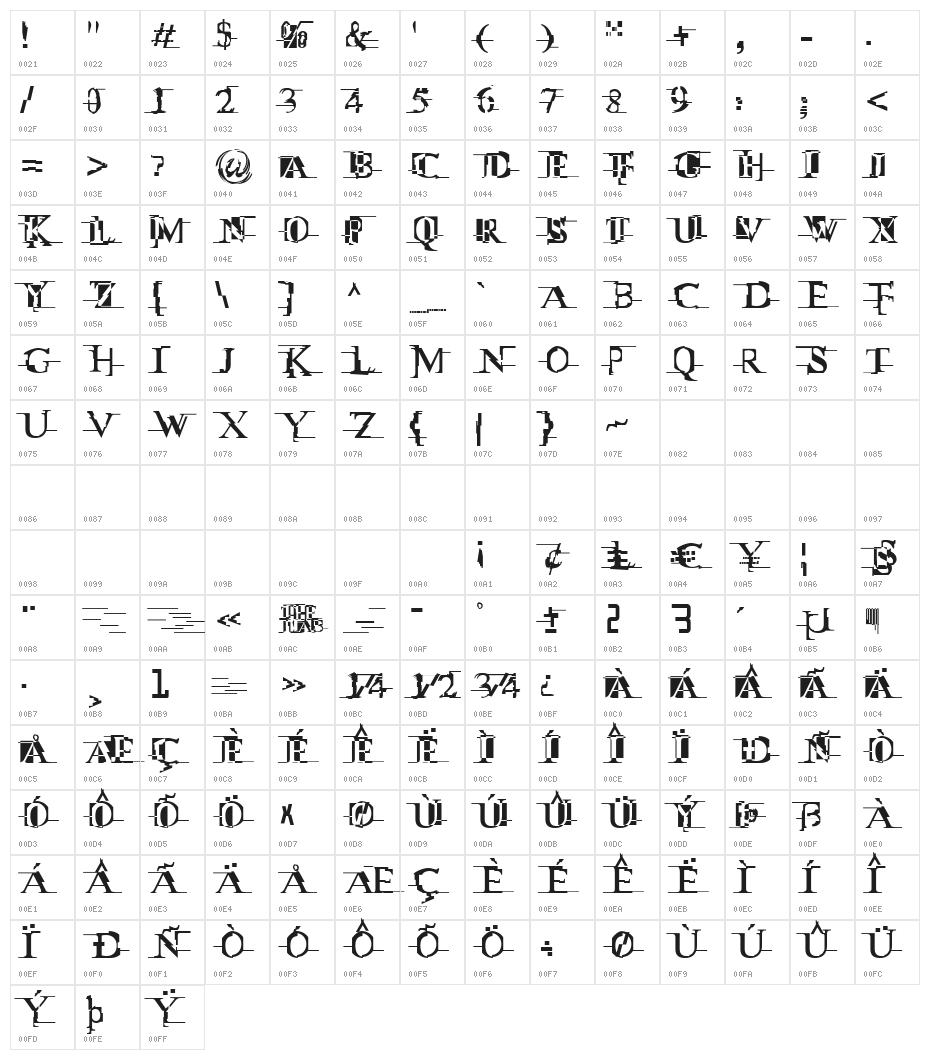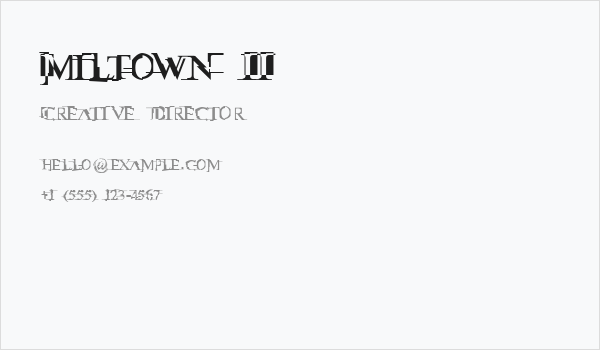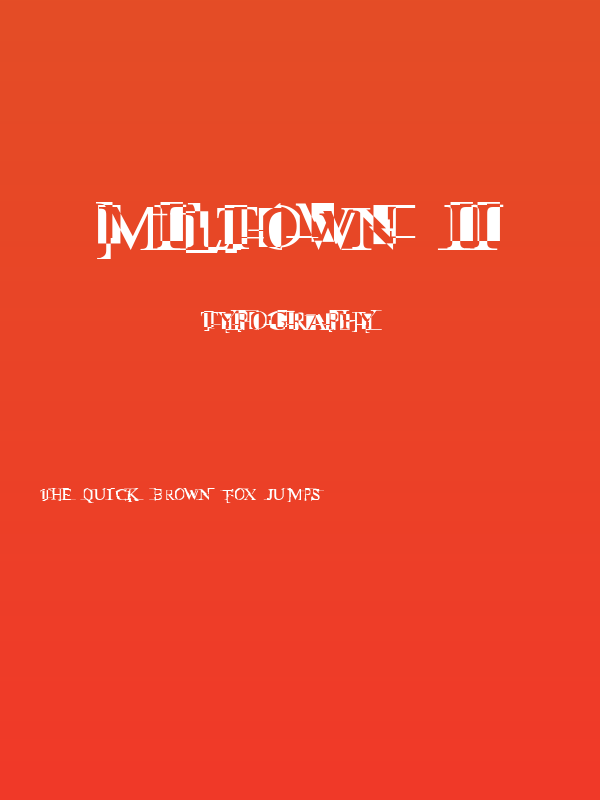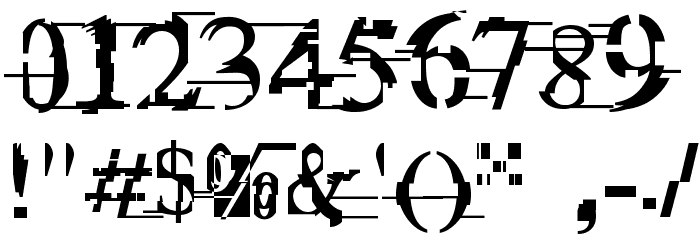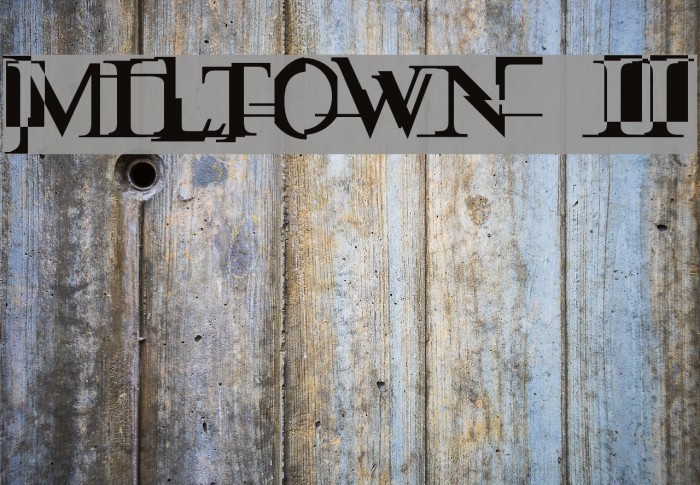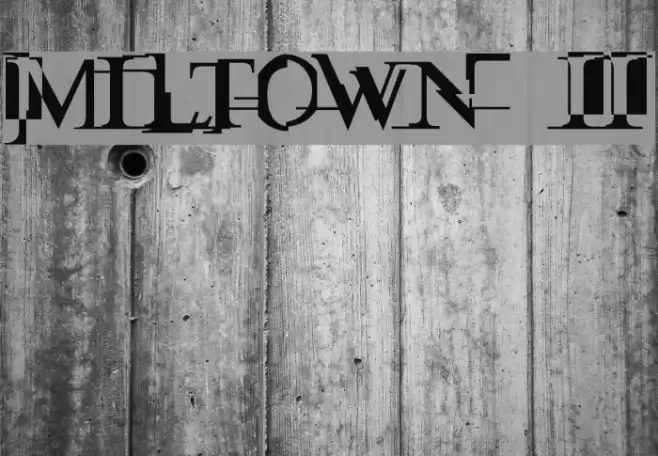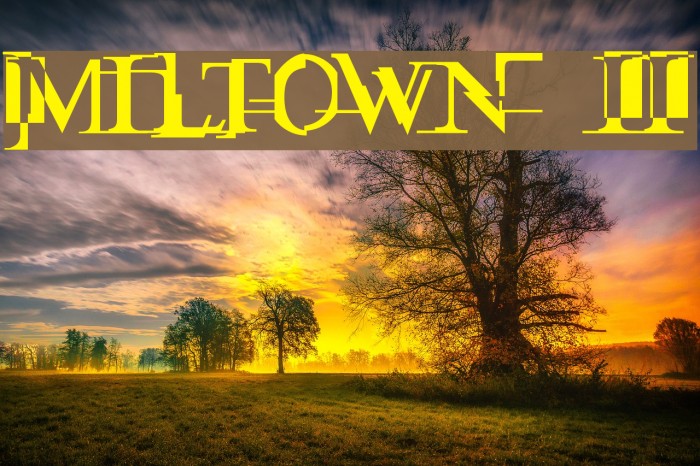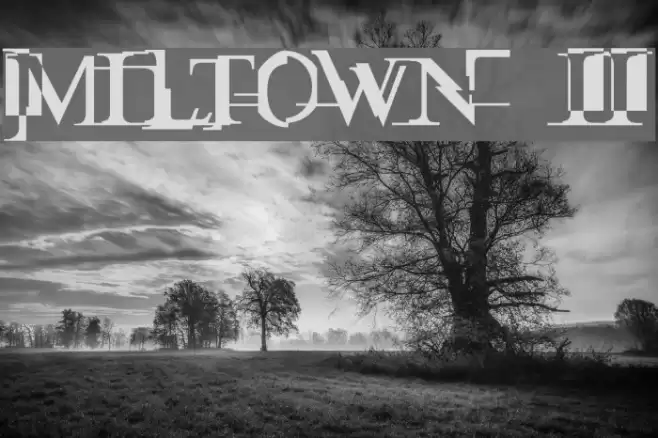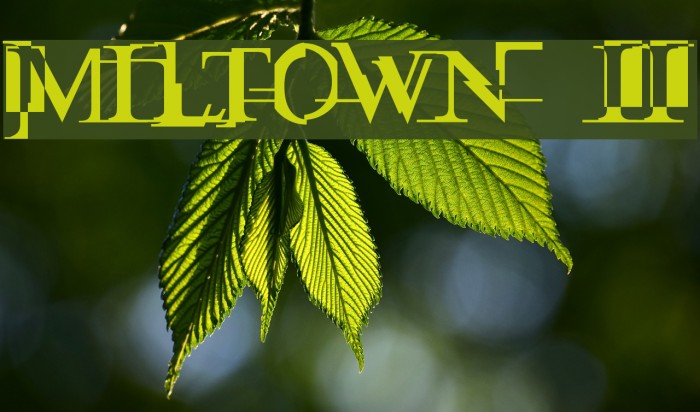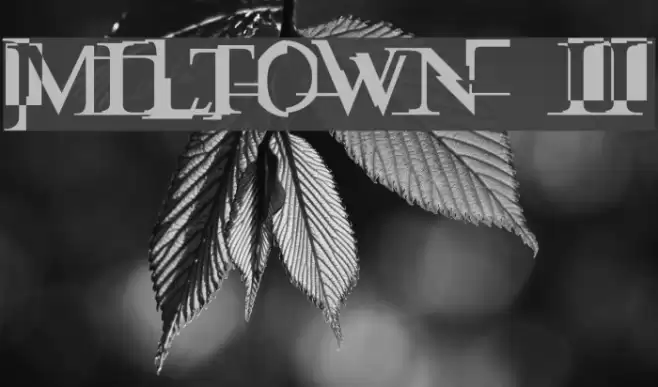
Miltown II Font
| Gesamtstil | Modern, Decorative |
| Vorgeschlagene Projekte | Ideal for album covers, posters, digital art, and branding that seeks a modern, edgy aesthetic. |